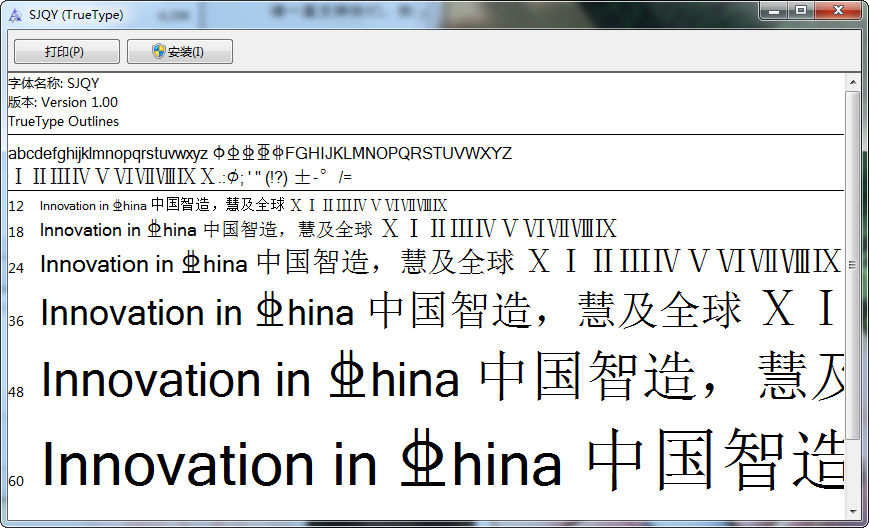
stqy鋼筋符號(hào)字體是一款常用的鋼筋符號(hào)字體,可以在word,office,PS中輸入鋼筋符號(hào),這款word鋼筋符號(hào)字體,在使用WORD時(shí)插入符號(hào),在SJQY里即可找到.小編這里提供stqy字體包下載,一共有4個(gè)級(jí)別鋼筋字體,歡迎下載使用。